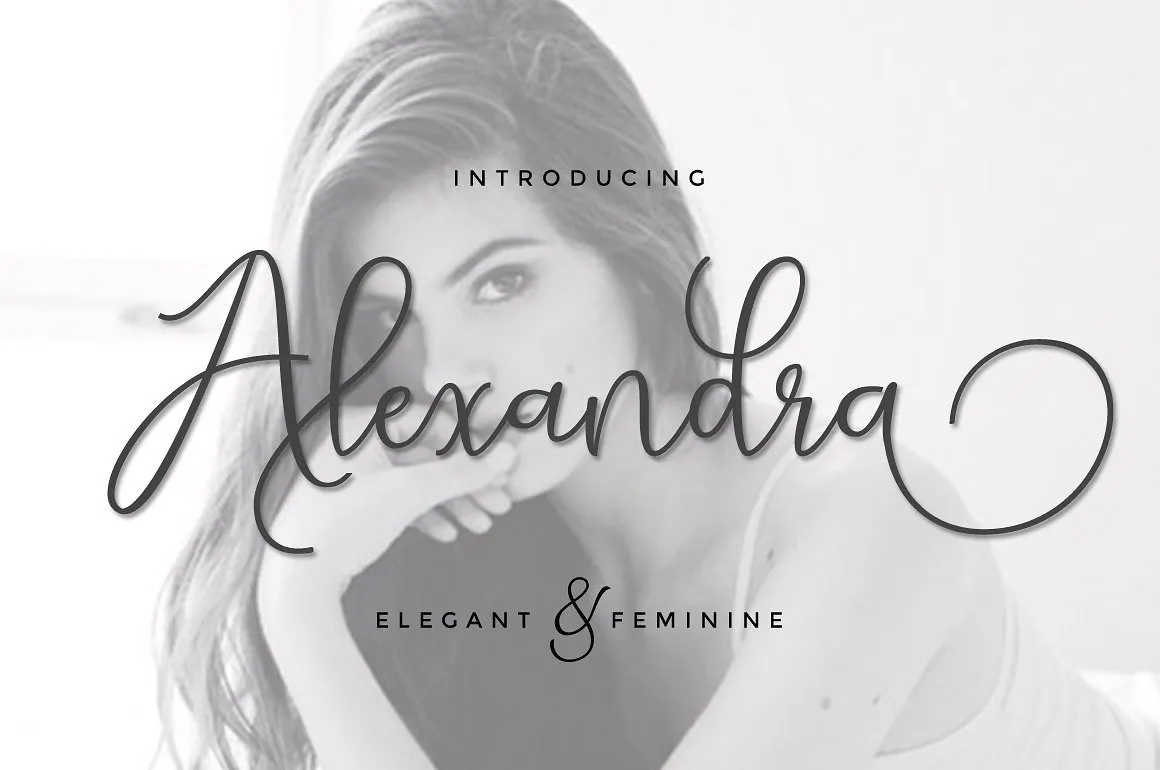
Alexandra Script Font – Download Grátis
A Alexandra Script Font é uma moderna tipografia de calligrafia, criada pelo designer Hamilton. Esta fonte moderna tem uma beleza casual que combina bem com estilos contemporâneos de script atualmente em alta. Seu design permite um uso versátil, desde as marcas e identidades visuais até a produção de itens pessoais como anotações diária ou caixas de lookbook. O estilo da Alexandra é perfeito para criações que buscam uma aparência glamourosa e sofisticada, seja ela num brochura de revista, um cartão de aniversário, ou até mesmo em uma apresentação elegante. A fonte exala versatilidade e facilmente se adapta a diversos tipos de mídia e projetos, garantindo que o estilo da Alexandra combine perfeitamente com qualquer projeto visual.